Poster memiliki kombinasi gambar, tipografi, warna dan efek visual yang disusun menarik agar mengkomunikasikan pesan dengan baik. Dalam poster seringkali menggunakan kombinasi gambar menarik sesuai tema desain agar memikat perhatian dengan cepat, terutama untuk promosi brand. Style font desain poster untuk tema dan jenis brand berbeda akan tampil dengan jenis font berbeda.
Perbedaan gaya tipografi akan menciptakan desain poster yang relevan sesuai pesan yang ingin disampaikan oleh brand. Pemilihan gaya font akan menyesuaikan jenis brand dan karakter brand, apakah serius, elegan atau santai. Terkadang pemilihan font juga menyesuaikan tema desain poster entah itu modern, minimalis atau klasik.
REKOMENDASI FONT POSTER UNTUK TEMA & BRAND BERBEDA
Untuk desain poster, gaya font yang menarik harus memiliki gaya huruf unik, menonjol tetapi juga mudah untuk dibaca. Font untuk desain poster seringkali memiliki font tebal, besar dan unik agar menarik perhatian. Poster untuk branding akan memiliki font yang sesuai jenis brand dan tema desain.
Raven untuk Tema Futuristik
Gaya font modern yang memiliki huruf tebal ini tampil dan akan efektif digunakan untuk menarik perhatian. Gaya huruf memiliki keunikan beberapa diantaranya terpotong pada bagian tertentu. Font juga memiliki beberapa huruf yang tersambung, namun karena huruf tebal dan sederhana, font memiliki keterbacaan yang baik.
Font yang tebal, tajam dan berkesan kaku tersebut cocok untuk digunakan sebagai font desain poster bertema futuristik. Poster untuk promosi brand teknologi atau event teknologi futuristik akan tampil modern dengan font tersebut.
Brandon untuk Tema Sporty
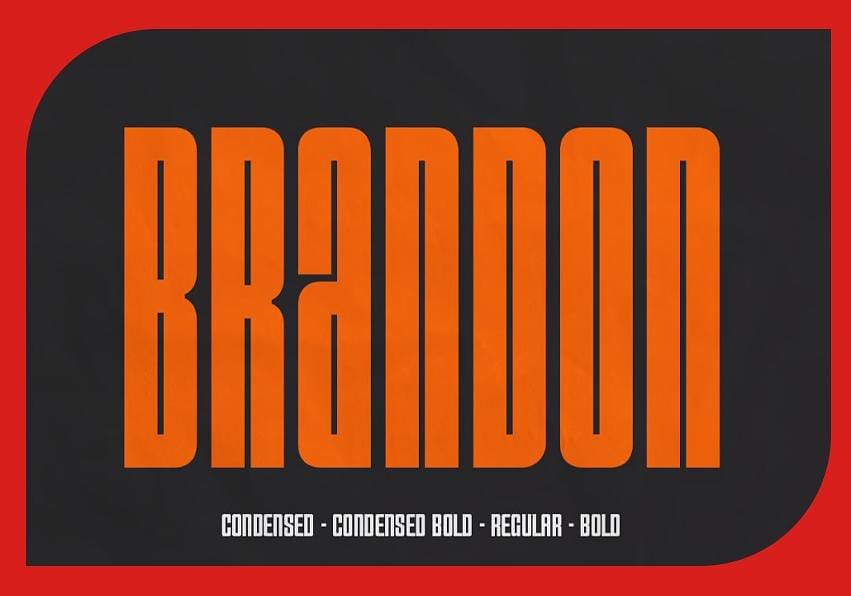
Font condensed yang memiliki huruf rapat dan ruang negatif yang sempit tersebut tampil bold. Gaya huruf tebal, tinggi dan rapat dapat menciptakan kesan tegas dan profesional pada desain poster. Cocok untuk merepresentasikan poster bertema sporty untuk brand fashion sport seperti jersey atau sepatu.
Font juga bisa digunakan untuk poster event olahraga yang bergaya modern dan profesional. Beberapa style huruf tersebut memiliki variasi berat bold, reguler, hingga condensed bold. Font condensed hanya efektif untuk digunakan sebagai font headline yang berkesan energik.
Aqila untuk Tema Fashion
Untuk desain poster, brand fashion dengan tema elegan, gunakan gaya font elegan yang unik. Font tersebut termasuk font condensed yang bertema elegan sehingga tampil tinggi. Font poster sering menggunakan gaya font condensed untuk menciptakan tipografi yang menonjol.
Gaya huruf tersebut memiliki tampilan elegan dan menciptakan kesan feminim sehingga bisa digunakan untuk poster brand fashion. Font memiliki tampilan tipografi yang berkesan mewah sehingga bisa menciptakan tema desain poster yang mewah.
Omica untuk Tema Minimalis
Untuk tema desain poster minimalis, gunakan font bergaya sederhana dan bersih seperti font omica tersebut. Gaya huruf memiliki style condensed tetapi masih memiliki ruang negatif yang cukup sehingga lebih mudah dibaca. Pada tema desain minimalis yang bersih dan penggunaan elemen sederhana, font akan mendukung tema minimalis.
Desain poster minimalis akan berfokus pada pesan utama tanpa terganggu elemen lainnya. Font sederhana tersebut akan membantu pesan utama dalam poster mudah terbaca dan efektif menyampaikan pesan. Font tersebut bisa dikombinasikan dengan font sans serif regular agar harmonis.
Krick untuk Brand Makanan
Font bergaya unik tersebut akan meningkatkan daya tarik visual desain poster, karena font tebal, sederhana dan guratan yang unik. Penggunaan font display tersebut bisa digunakan untuk merepresentasikan desain poster brand makanan atau tema makanan. Untuk promosi brand makanan, font akan tampil hangat, menonjol dan unik.
Seringkali gaya font tersebut ditemui pada desain logo kemasan makanan, untuk itu juga relevan untuk branding poster makanan. Sebagai font headline, tipografi akan menonjol dan bisa menjadi pusat perhatian utama. Cocok untuk font dikombinasikan dengan warna kuning atau oranye yang berkesan hangat.
Cathy untuk Brand Kosmetik
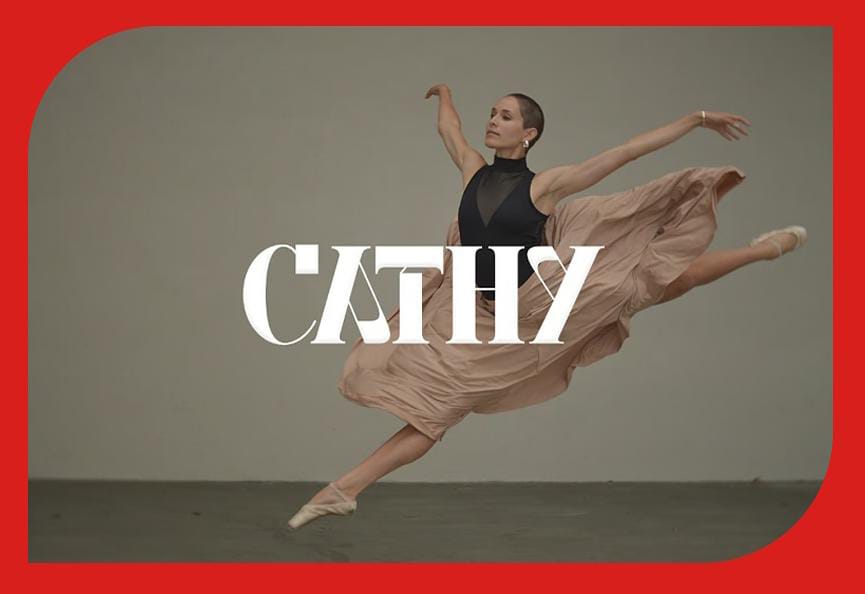
Untuk desain poster bertema kecantikan gunakan gaya font yang elegan, unik dan memiliki garis yang kontras. Font memiliki gaya huruf kontras dengan garis tipis dan tebal yang menciptakan kesan elegan. Font brand kecantikan yang elegan akan merepresentasikan kesan yang feminim.
Gaya huruf yang kontras dan unik tersebut bisa membuat poster brand kecantikan tampil menonjol. Brand kecantikan seringkali menggunakan font serif atau script yang elegan untuk desain posternya agar relevan. Kombinasikan font elegan dengan font sans serif elegan agar kontras dan tampil harmonis.
Espansa untuk Brand Coffee
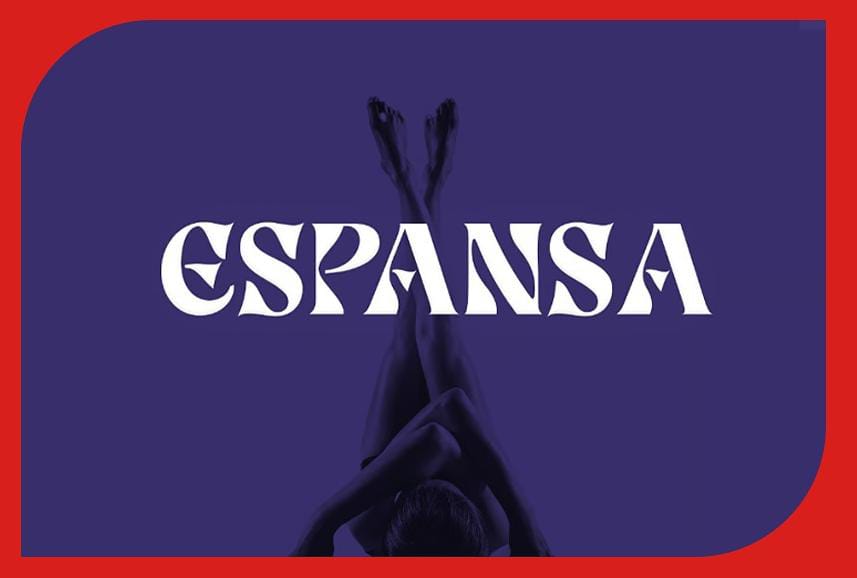
Style font dengan garis yang melengkung-lengkung seperti pada jenis font espansa tersebut cukup populer. Akhir-akhir gaya font tersebut banyak digunakan pada desain modern untuk poster, brand atau logo. Gaya huruf yang unik tetapi juga bersih tersebut memudahkan untuk dibaca.
Font yang unik untuk headline desain poster akan menonjolkan pesan utama dengan cepat. Gaya font yang unik tersebut akan cocok digunakan sebagai font poster untuk brand coffee sehingga tampil estetik. Gaya huruf melengkung menciptakan tampilan yang alami, relevan untuk brand coffee organik.
Baca juga: 6 Tipografi Gaya Font Old School untuk Desain Retro
TIPS KOMBINASI FONT DESAIN POSTER
Desain poster untuk tema modern dan klasik tentunya akan memiliki perbedaan gaya huruf yang mencolok. Namun berbeda lagi dengan kombinasi font yang diciptakan dalam desain poster juga harus kontras tetapi sesuai tema dan jenis brand. Kombinasikan font poster yang kontras, unik dan sesuai dengan pesan yang disampaikan dalam poster.
Kombinasi Gaya Font yang Kontras
Untuk menciptakan desain poster yang menarik perhatian, font yang digunakan harus memiliki gaya berbeda. Kontras tipografi dalam desain poster bisa diciptakan melalui perbedaan tebal, gaya huruf dan jenis font. Kombinasikan jenis font berbeda seperti font condensed bold dan font sans serif sederhana. Selain jenis font berbeda, bedakan ketebalan dan gaya hurufnya agar tampil kontras.
Font Judul Lebih Menonjol dan Unik
Perlu diingat jika font judul harus yang paling unik, menonjol, atau yang paling tebal biasanya. Sementara font lainnya bisa lebih sederhana seperti font judul menggunakan variasi bold, maka font sub judul bisa menggunakan font regular. Bentuk font yang unik akan membuat judul mudah menarik perhatian, namun pastikan tetap bisa dibaca.
Bedakan Ukuran Tipografi
Tidak hanya harus jenis fontnya berbeda, penting mengatur ukuran teks dalam desain poster. Selain perbedaan gaya hurufnya, bedakan ukuran teks judul, sub judul dan paragraf agar menciptakan hirarki visual. Perbedaan ukurannya juga harus proporsional tidak boleh sembarangan, karena bisa terlihat buruk jika terlalu berbeda.
Kombinasi Dua atau Tiga Font
Untuk desain poster jangan terlalu banyak menggunakan jenis font karena bisa tampak berantakan. Dua atau tiga font sudah cukup, pastikan kombinasi font tampak harmonis dan menciptakan keseimbangan visual. Gunakan font yang unik satu saja, lainnya bisa menggunakan style sederhana agar tidak menciptakan desain yang buruk.
Pemilihan font poster sebaiknya sesuai tema desain atau jenis brand agar relevan dan menciptakan desain yang menarik. Kombinasi font dalam desain poster harus unik dan menonjol. Terutama font utama harus disesuaikan dengan tema desain agar menarik perhatian dengan cepat. Rekomendasi beberapa gaya font untuk tema desain poster berbeda akan mempresentasikan pesan poster dengan baik.